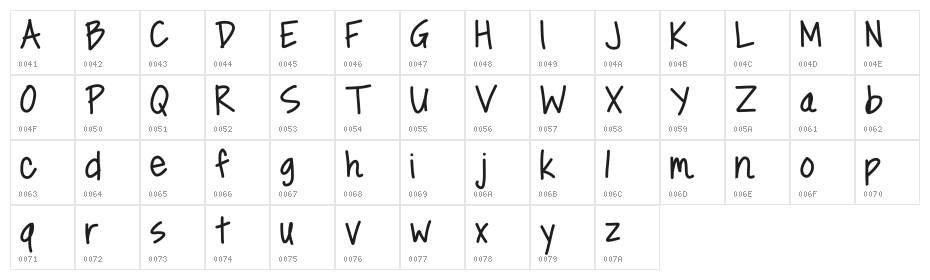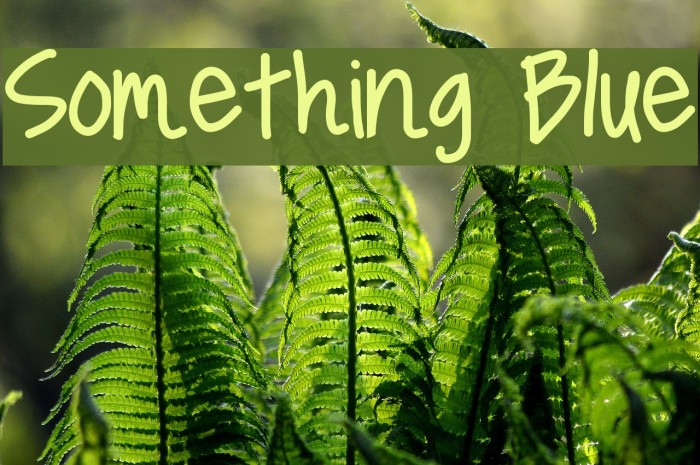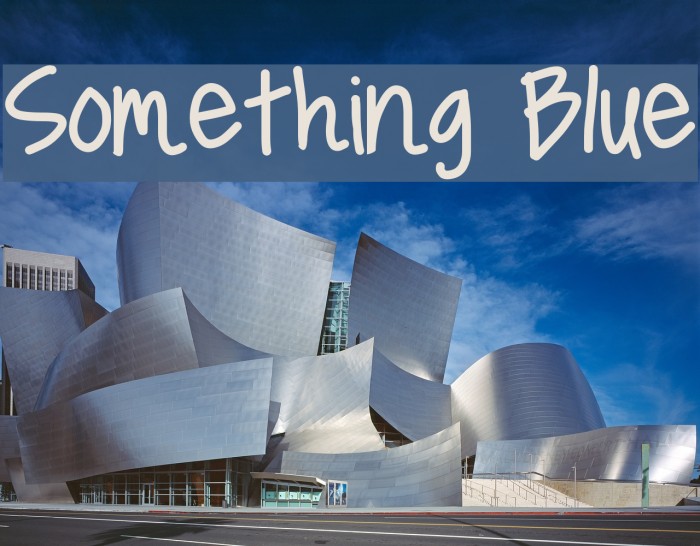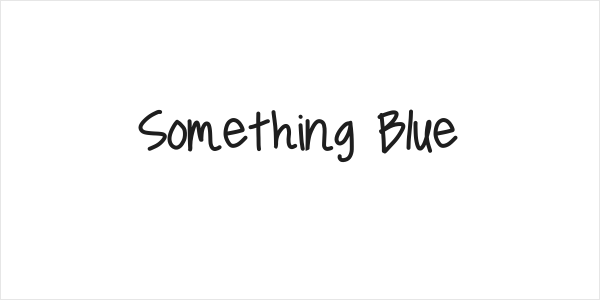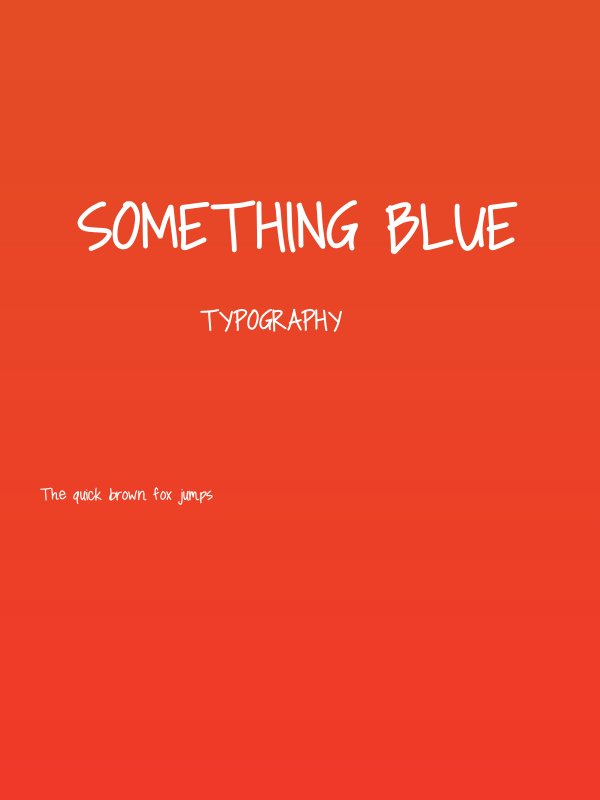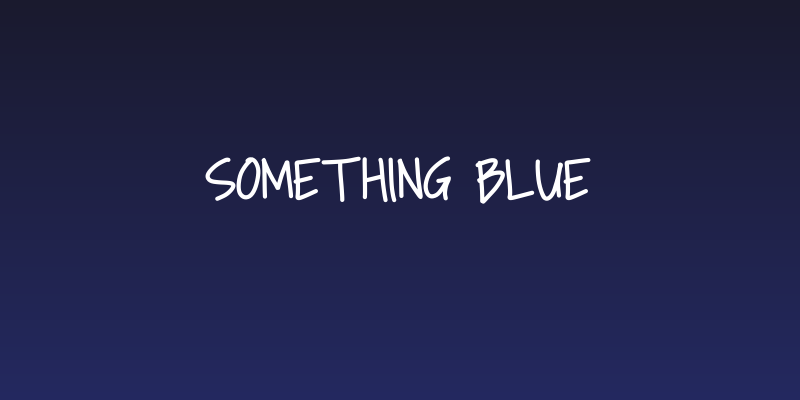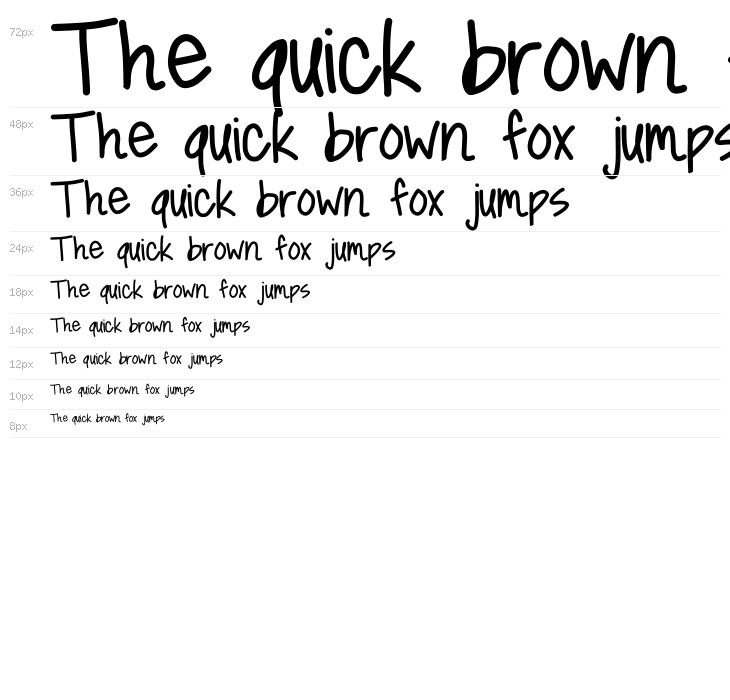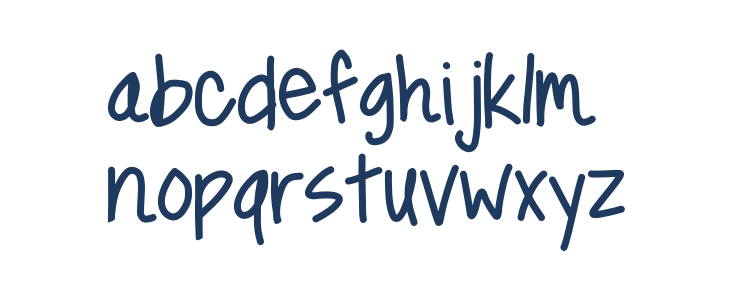
Something Blue Font
| Estilo geral | Casual |
| Caso de uso | Headlines, Logos, Informal Text |
| Projetos propostos | Ideal for greeting cards, invitations, children's books, and informal branding. |